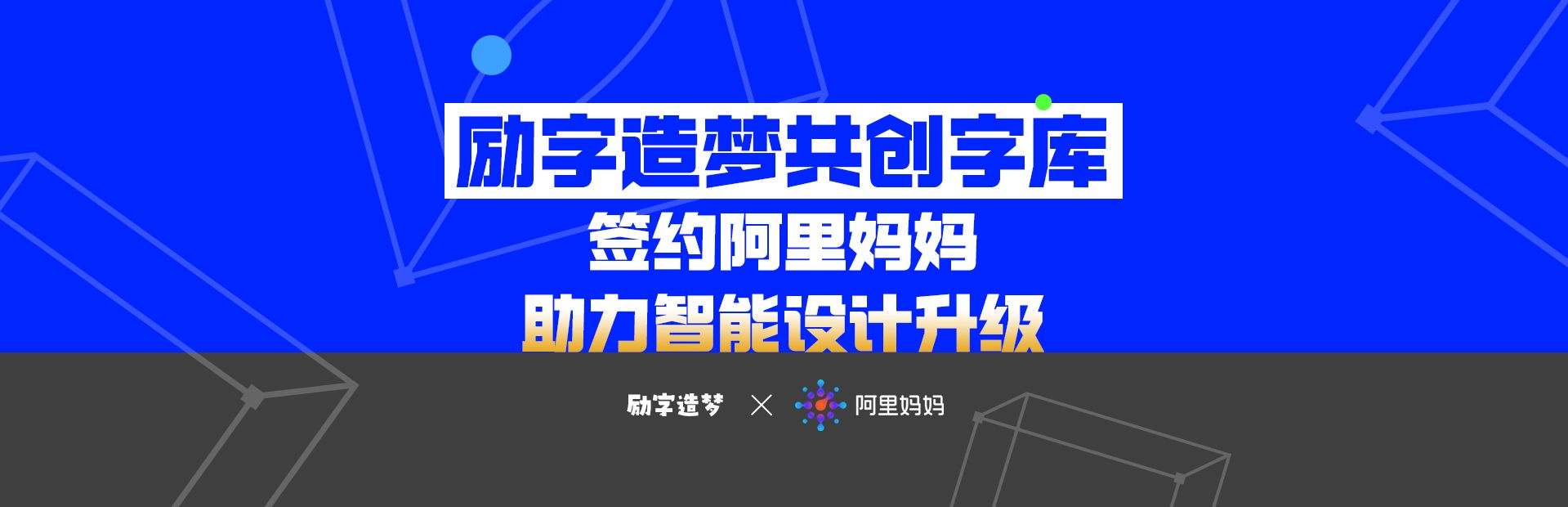
励字造梦共创字库签约阿里妈妈,提供汉字虫洞AIGC智能设计大模型通用字库解决方案,加速智能设计升级
伴随全球的数字化产业升级,智能设计成为当下潮流趋势。阿里妈妈整合全球优质营销资源,基于大数据、人工智能技术,提供亿级的专业性的营销洞察、运营工具及内容创作素材,为互联网生态提供营销、创作、设计、宣传、包装等商业化运营的全链路数字化生产,释放商业价值。
励字造梦共创字库签约阿里妈妈,为阿里妈妈创意中心平台提供汉字虫洞AIGC智能设计大模型通用字库解决方案,为阿里妈妈互联网产业生态提供高质量的字体,加速智能设计升级,为内容生态中的生产者与使用者提供全场景的字体应用,提升内容价值。
随着抖音、小红书、淘宝、天猫等全媒体平台的蓬勃发展,各类版权法规的落地,字体的使用场景迅速扩大,被广泛应用于广告制作、内容创作、品牌营销中,商用版权日益受到重视。作为内容生产中最重要的生产资料之一,优质适配的字体能带来更好的用户反响和商业化效果。优质的智能设计平台也能帮助创作者快速找到高质、适配、有保障的内容素材。
此前,励字造梦共创字库已与创客贴、稿定设计、兔展、水母智能等平台合作。此次与阿里妈妈的授权合作的智能设计大模型字库,授权字体涵盖 VLOG、电商、短视频、游戏、海报、印刷、综艺等全媒体场景,涵括现代、创意、可爱、国风、潮酷、个性、酸性、古典、文艺等不同风格,以应对阿里妈妈各类创作者客户多样化的字体需求。